今天文章将介绍拉丁字母的样式,并了解它的历史内涵和样式特征,其中包括被我们熟知且最容易想到的Sans、Serif、Script和Slab这四种字体。还有Official Vox/ATypI、British Standard、Gerrit Noordzij理论分类体系。这是重要的字体基础知识,建议收藏学习。
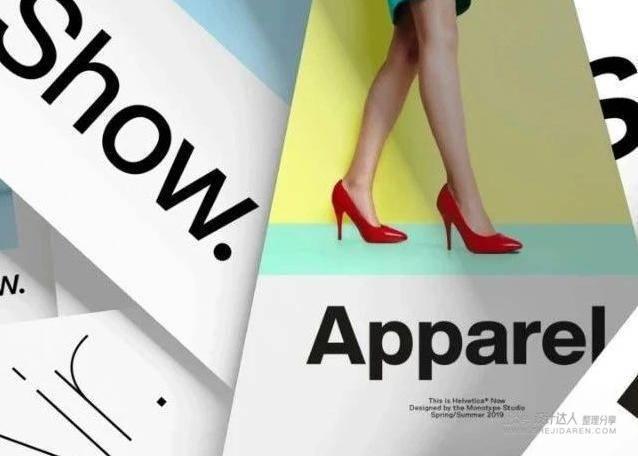
这种字体样式是从书法字体演化而来的第一种Roman字体。因此,在这种字体中,字母的形状与扁刷或扁头笔的正式书写体相似。通常情况下,Humanist常用于Serif字体设计。而现今,也有人将Humanist用于Sans字体。
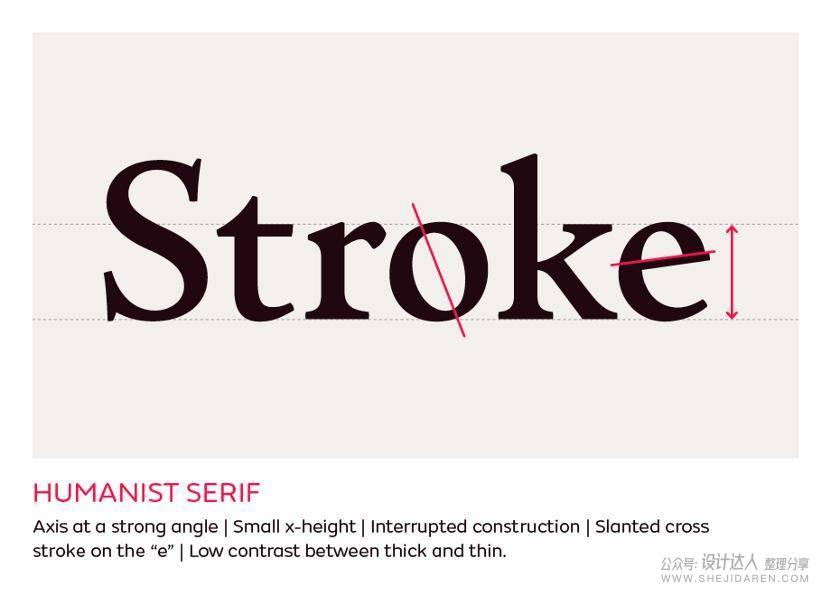
特点:轴倾斜角度较大,小写字母“x”字高较低,间断型设计。小写字母“e”中线略微倾斜,笔画粗细对比度较低。
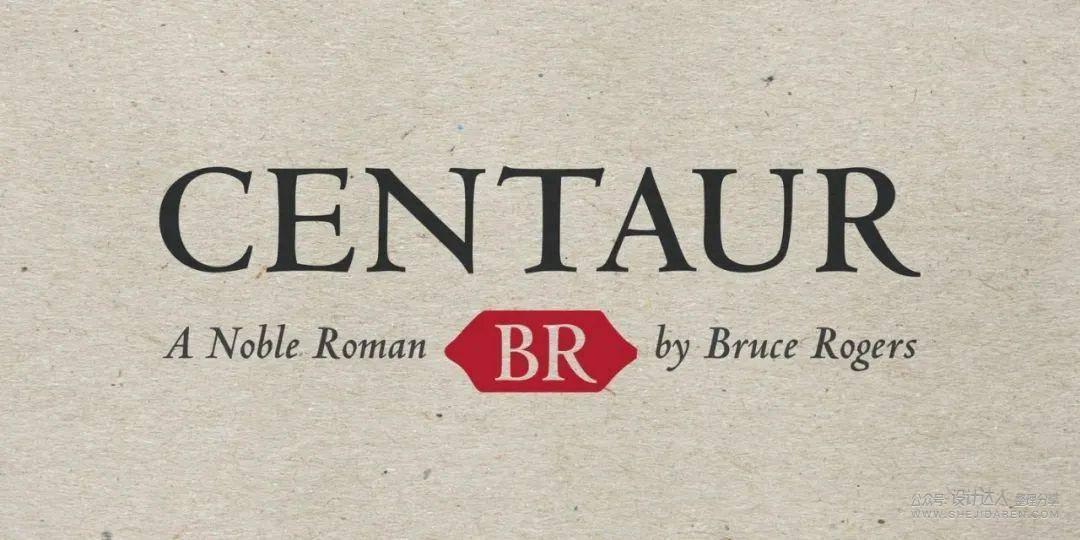
Centaur
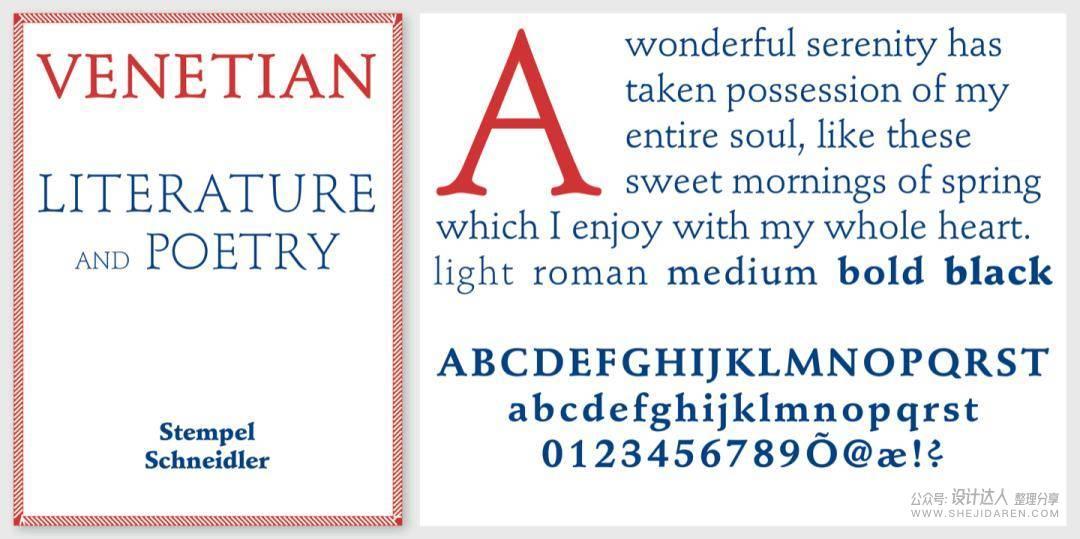
Stempel Schneidler
这种字体样式以15世纪末至18世纪间两位著名的字体设计师命名——法国字冲雕刻师Claude Garamond和威尼斯印刷师Aldus Manutius。Garalde字体样式是Humanist字体样式的进一步拓展,但仍受正式书法的影响。在15世纪末至18世纪间,印刷和字冲雕刻方面的许多技术的改进为诸多字体的发展和诞生提供了契机,这些焕然一新的字体现在仍在书本或长文本的排版工作中广泛使用。这种字体样式也称Aldine(以Aldus Manutius命名),有时还被称为Old-Style,该词有时也会用于Humanist、Garalde和Transitional字体。
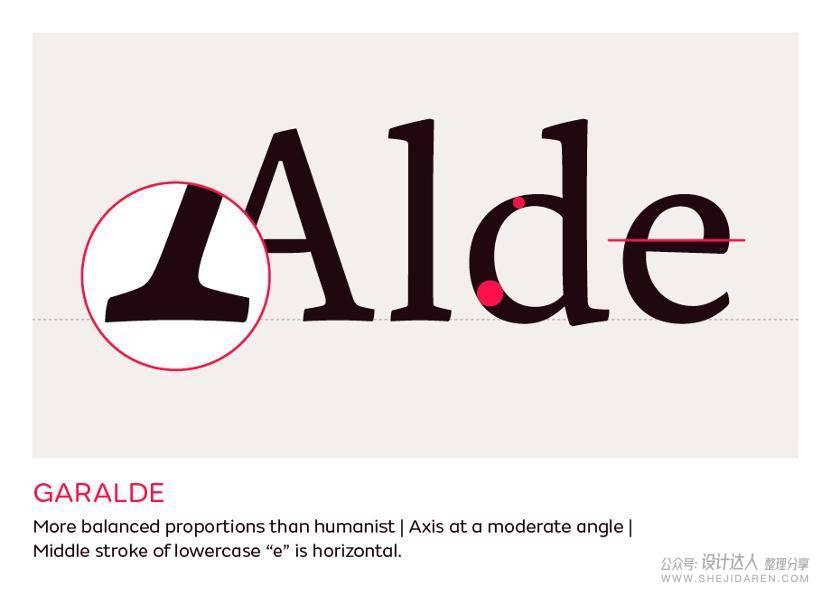
特点:与Humanist相比,比例更均衡,笔画粗细对比度更高,轴倾斜角度适中,衬线形状更统一,小写字母“e”的中线呈水平状。
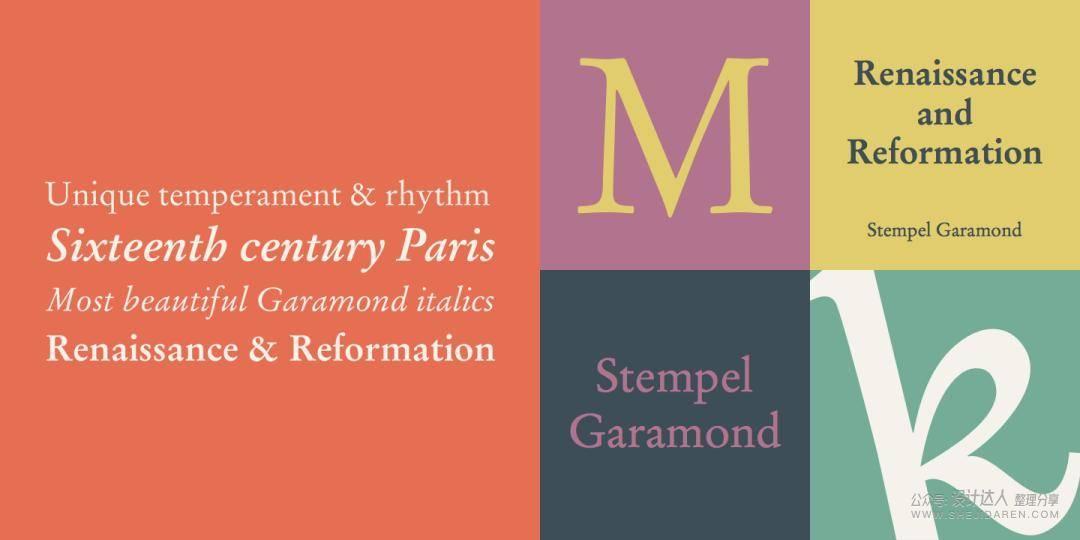
Garamond
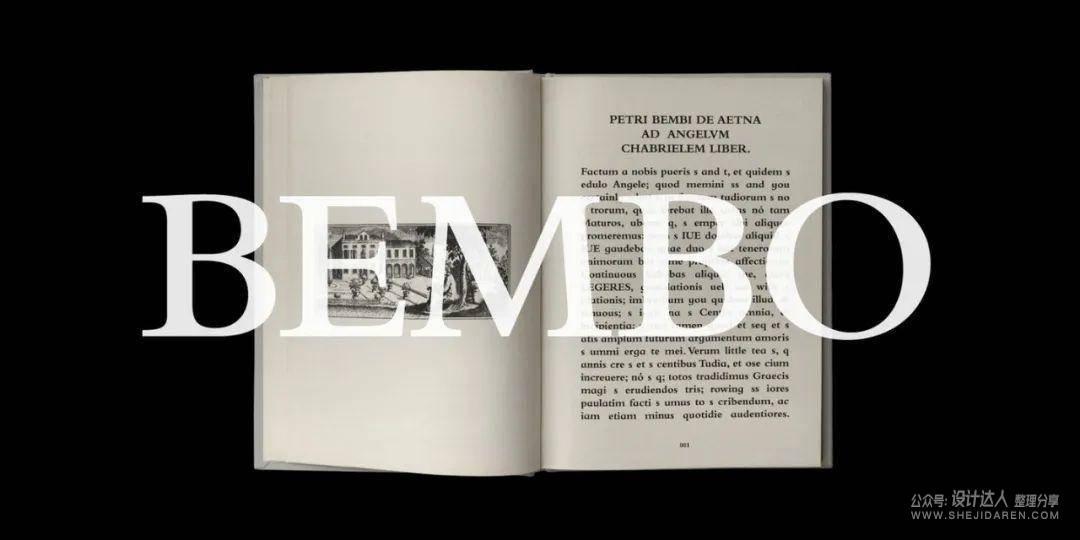
Bembo
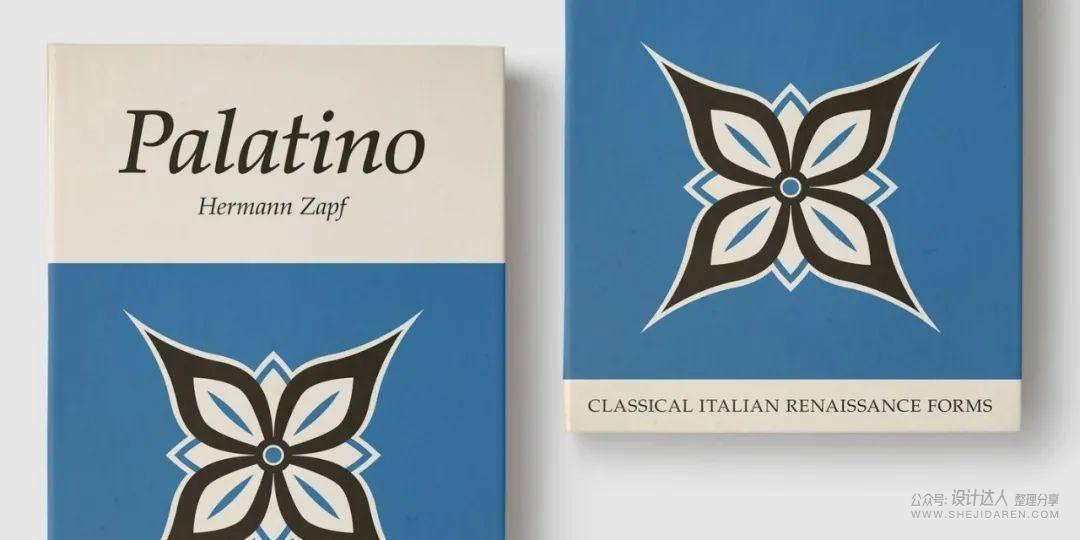
Palatino
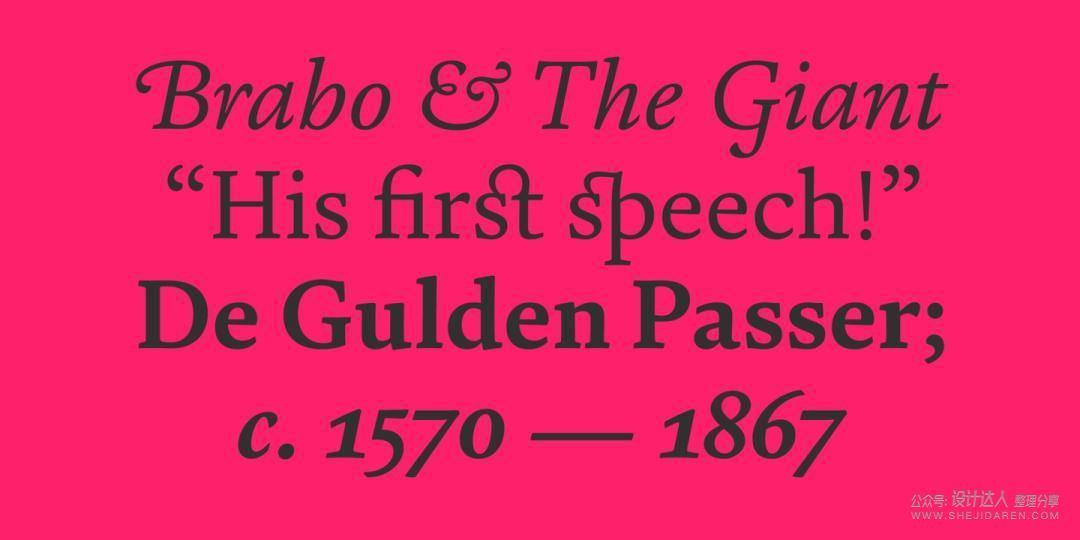
FS Brabo
在17世纪末,法国国王路易十四希望对法国政府(皇家帝国)使用的印刷机进行翻新,寻找可以替代Garamond字体的其他字体,进而与当时欧洲各地的印刷品质竞争。国王委托法兰西科学院创造了一种新的字体,即Roman du Roi –86字体。这种字体是根据严格的网格、数学和工程学体系设计的。这一时期著名的字体设计师有John Baskerville、Simon Fourner和Christophe Plantin。Transitional字体样式的另一个名称是Realist,源自西班牙语中指代“Royal”的词汇(所以其实与现实主义无关),因为该字体是Christophe Plantin为西班牙国王菲利普二世设计的。
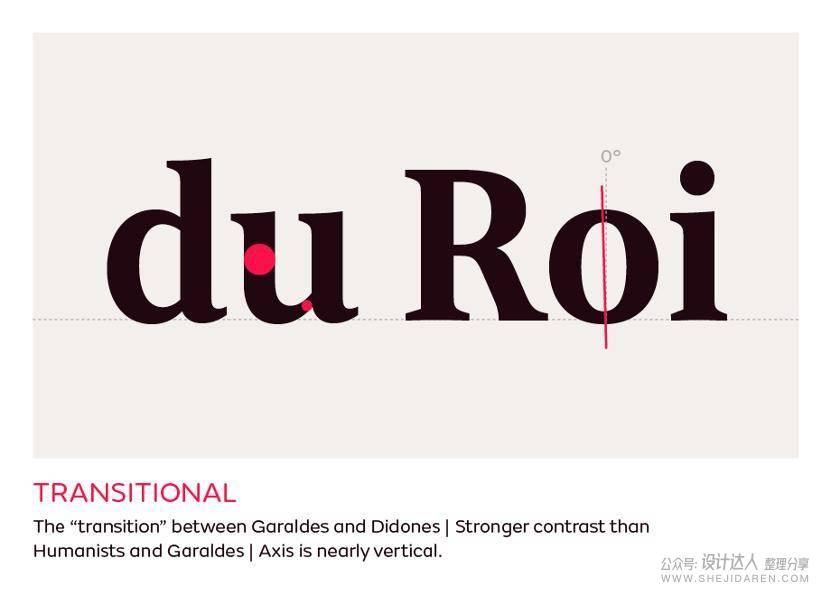
特点:Garalde和Didone之间的“过渡”,笔画粗细对比度比前两组强。重点轴线逐渐从强势的书法角度转至现在几乎垂直的角度。衬线更为平滑,细节之处更为精致。如果将Transitional字体样式看作是老式字体与现代字体之间的“过渡”,那么,在实际的使用中就能够很容易地识别这种类型的字体。
Baskerville
FS Neruda
Joanna
Melior
Didone取自创作人Firmin Didot和Giambattista Bodoni的名字。两位创作人技艺不凡,二人在专业上的切磋,促成了字体设计、字冲雕刻和印刷等领域的突破。Didone字体也被称为“Modern”字体,但是由于容易与“modern”和“contemporary”等形容词混淆,所以大多数情况下不使用“Modern”这个叫法。
特点:字体的线条笔画粗细对比度极高。前几组衬线字体的书写采用的是扁头笔,而Didone字体则选用了尖头笔,且书写角度为90度,笔画水平,线条纤细。Didone字体的衬线纤细,无弯曲。该款字体在2017年可谓十分潮流,很有现代气息。但事实上,这种字体的根源可以追溯到18世纪中期。
Bodoni
Didot
FS Ostro
Walbaum
Slab字体还有许多别名:Mechanical / Mechanistic、 Antique或Egyptian。这种字体的特色是块状粗矩形衬线,最初用在广告、海报和大型媒体中,可以吸引注意力。Slab字体突出了19世纪初工业革命的精神,是大型展览中的专用字体。类别上,Slab字体包括方形直衬线字体(通常被称为Egyptians字体)以及弯衬线字体(Clarendons或Ionics字体)。
特点:粗衬线,小写字母“x”字高较高,线条粗细对比度低,凸显字体丰度,让字体尽量占满空间。除衬线弧度上有明显的不同以外,Egyptians字体更加规矩周正,Clarendons的衬线则带有一定的弧度,更显得精致柔和。
Memphis
Rockwell
Clarendon
FS Silas Slab
Grotesque是一种起源于19世纪的无衬线字体。
特点:由于Grotesque字体是由早期无衬线字体演变而来,故这种字体往往具有许多独特的特征。比如,笔画粗细对比度不一,有时有粗细对比,有时又显得古怪夸张,完全不符合书法字体的笔画粗细对比逻辑。圆形和笔画弯曲之处比较周正,笔画端点或水平或带有弧度。大写字母“G”通常有竖线延伸,而大写字母“R”的右下尾端时常有弧度变化。
Franklin Gothic
FS Meridian
Venus
Neo-grotesque
Neo-grotesque字体是Grotesque在后续发展中衍生出来的一种新字体,其类别包含了一些较为流行的无衬线字体:Helvetica字体和Univers字体(许多不同的电子版本与原版的差距较大)。两种字体的设计遵循简约风的思路,字体磅数和宽度存在多种变化,形成可用于不同场合的不同系列。
特点:笔画粗细对比度低,比例和形状更为协调,更有规律可循。与Grotesques不同,Neo-grotesque字体的大写字母“G”没有竖线延伸,小写字母“g”通常是单层的。
Helvetica
Univers
DIN
FS Elliot
无衬线字体灵感来自简单的几何图形。Geometric字体的设计虽看起来较为简易,但其中不乏微妙的视觉微调,使得字形简约纯粹。
特点:笔画粗细对比度最小,构造以重复的图形(如圆形、正方形和三角形)为特色。最常见的就是单层的小写字母“a”和“g”,单层的设计与几何从简风格完美搭配,相辅相成。
Bank Gothic
FS Lucas
Futura
Humanist Sans
如前所述,Humanist Serif字体深受扁头笔书法的影响,而Humanist Sans字体就如同Humanist Serif的兄弟一般,在诸多方面都大同小异。
特点:Humanist Sans字体与Humanist Serif特征几乎相同,但最大的区别在于没有衬线。相比之下,Humanist Sans的笔画粗细对比度通常要低得多,但这种对比度仍清晰可见,以角度上的对比较为突出,只是没有经典的Humanist Serifs字体表现得那么淋漓尽致。字体的比例设计源于经典的Roman字体。书法对字体的影响在字体的构造、开放的字腔、笔画间连接的角度以及常见双层的小写字母“a”和“g”的选择等诸多方面上一目了然,足见影响之深远。因此,相比于无衬线的Grotesque字体和Geometric字体,Humanist Sans字体更适合与阅读相关的用途。同时,Humanist Sans字体使用的斜体通常是草书体,而不简简单单是倾斜的Roman字体。
FS Millbank
FS Siena
Gill Sans
Johnston
Script字体带有浓重的手写风格,可以根据不同的手写工具加以区分,如毛笔、马克笔或尖头笔等。
特点:灵感源于不同的手写风格。Script字体的字母通常相互之间没有间隔,且较为倾斜,如同草书一般。这种字体既可以如同经典书法一样规矩板正,又可以如同普通书写一样随意俏皮。许多Script字体需要其设计者为每个字母绘制多个版本,进而再度展现手写体不拘一格的外观与活力。